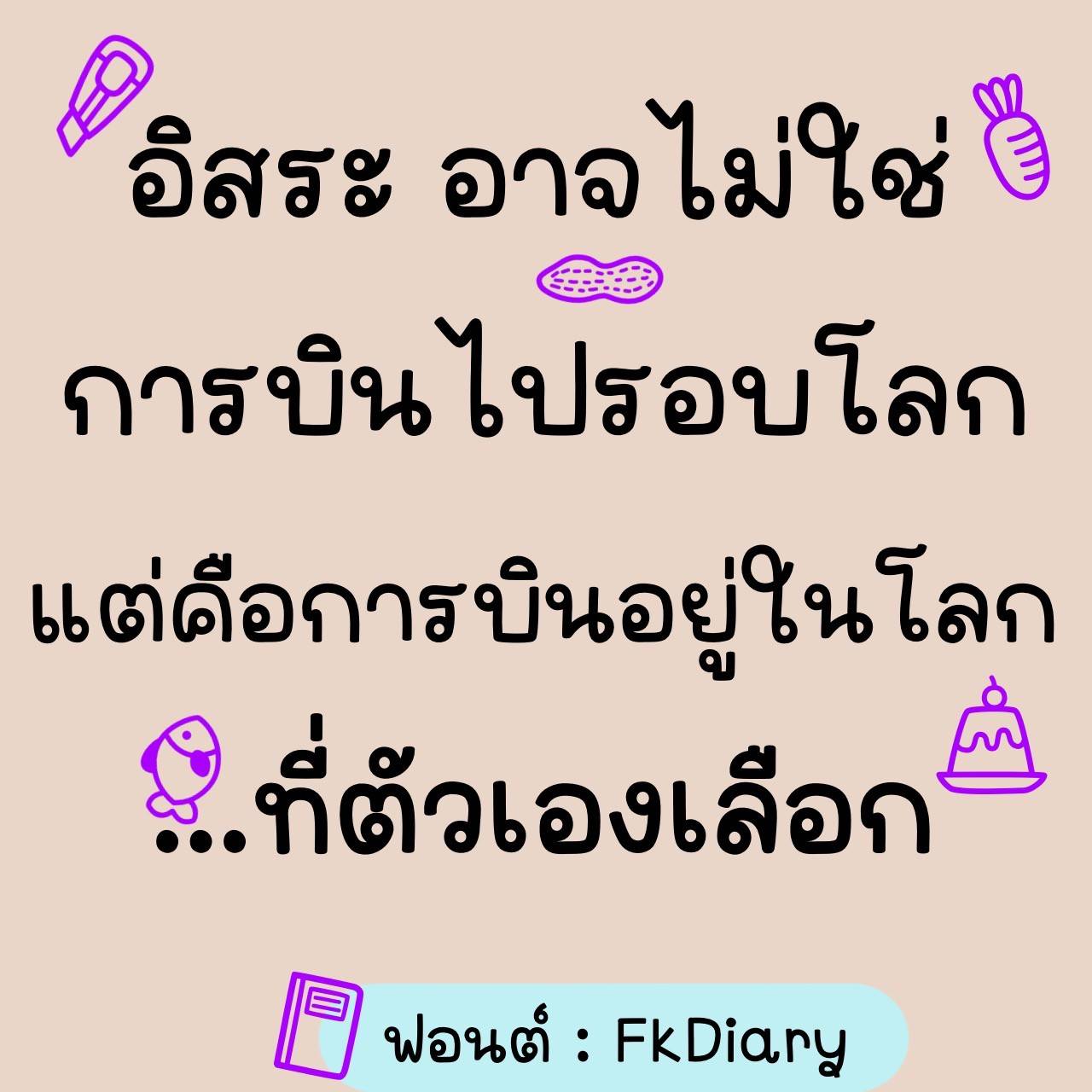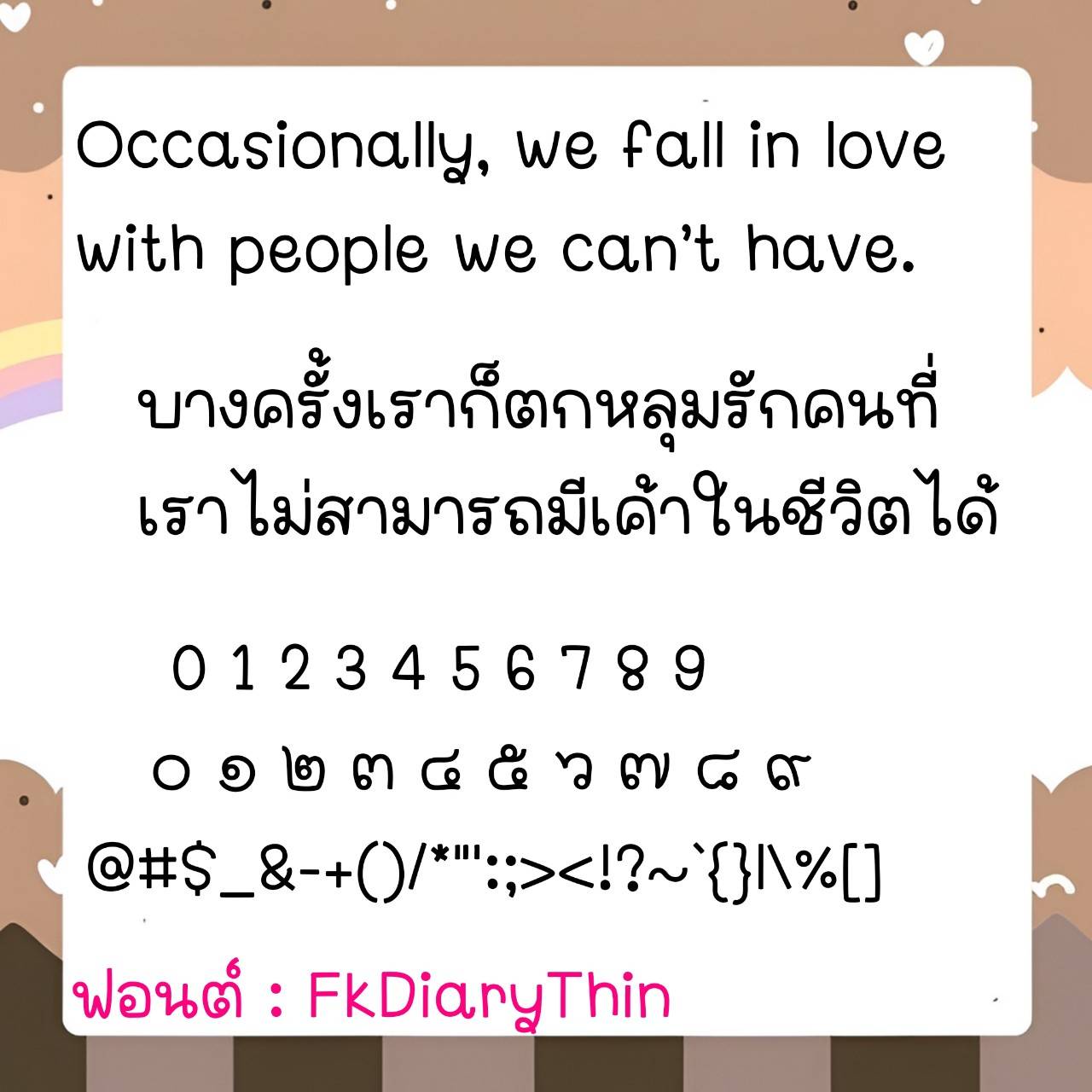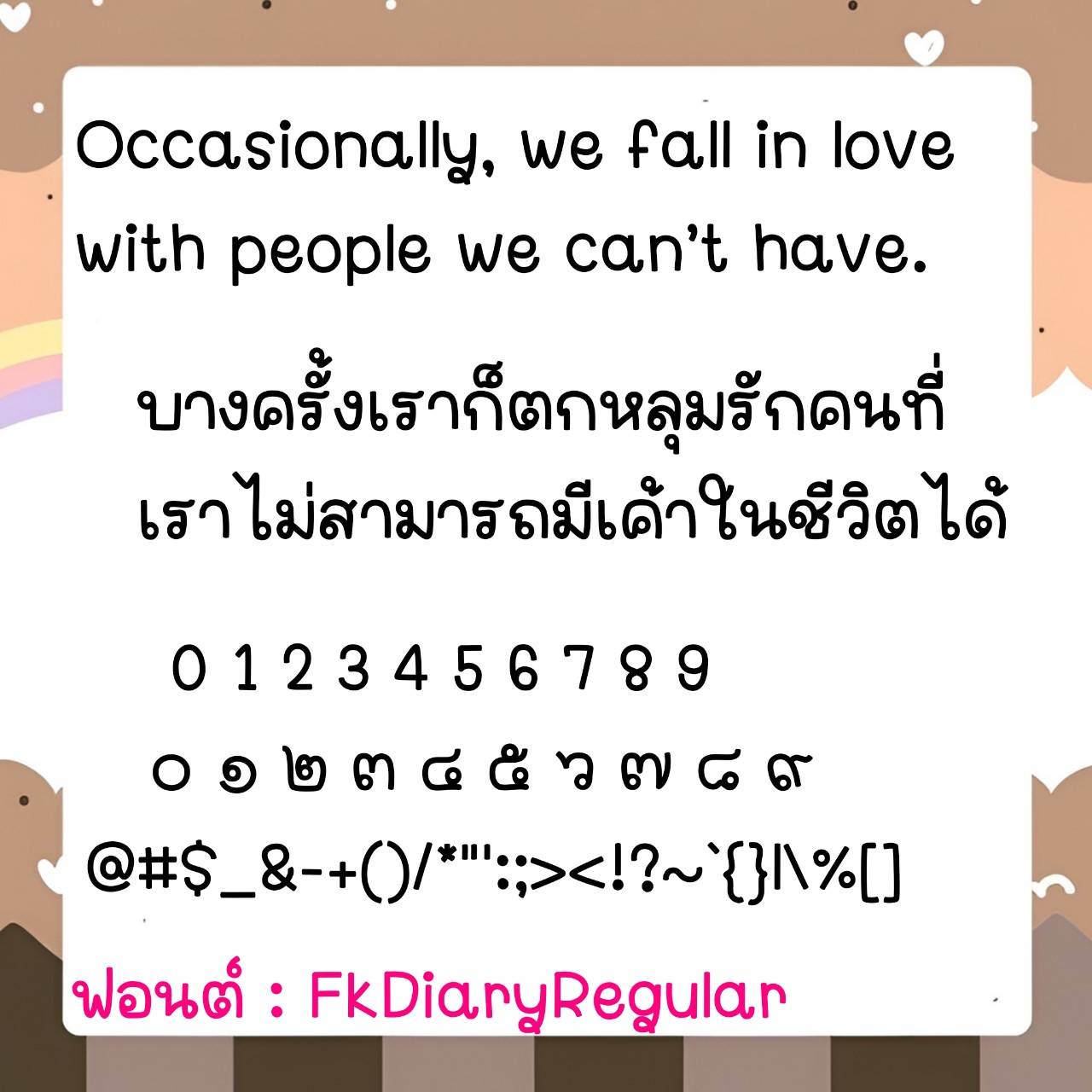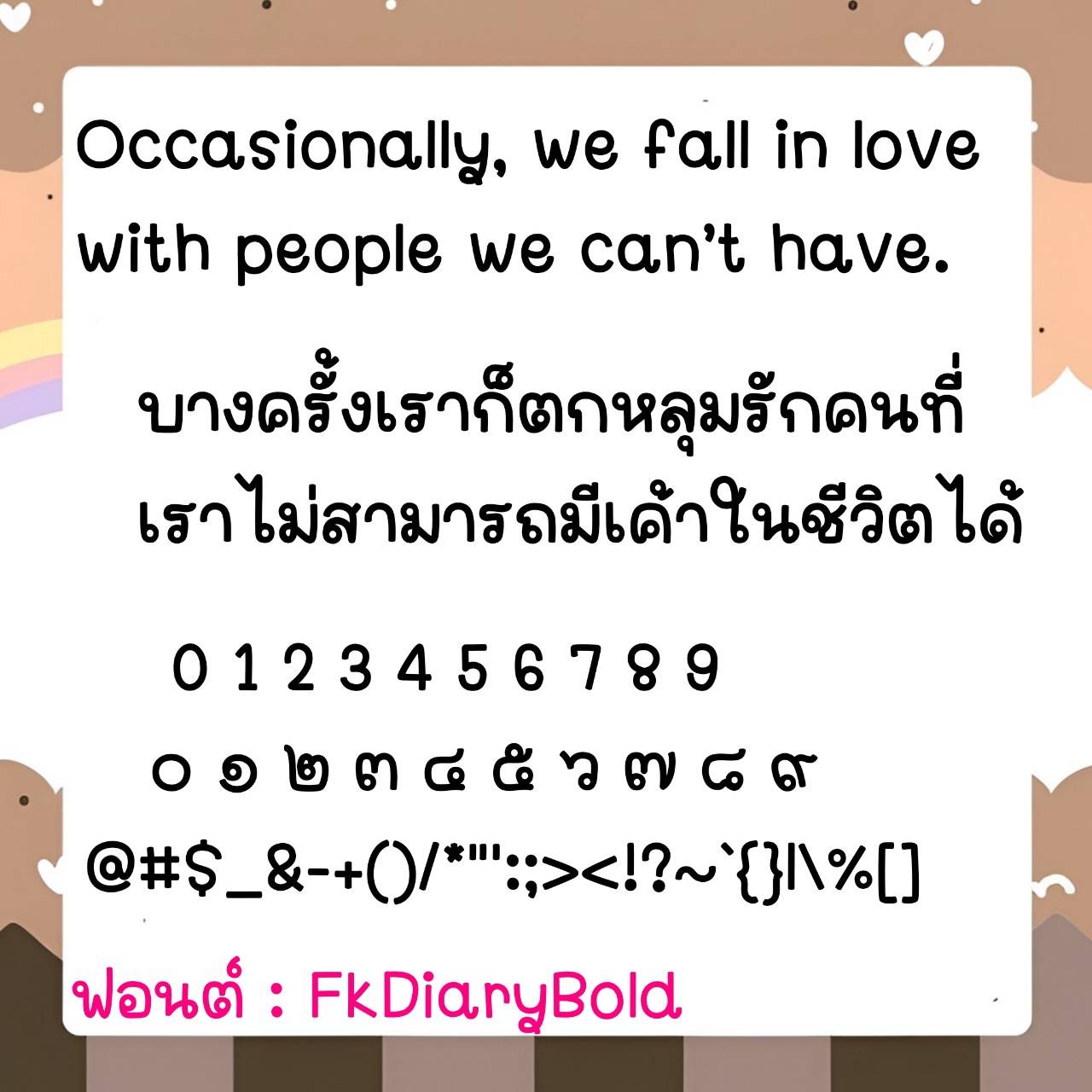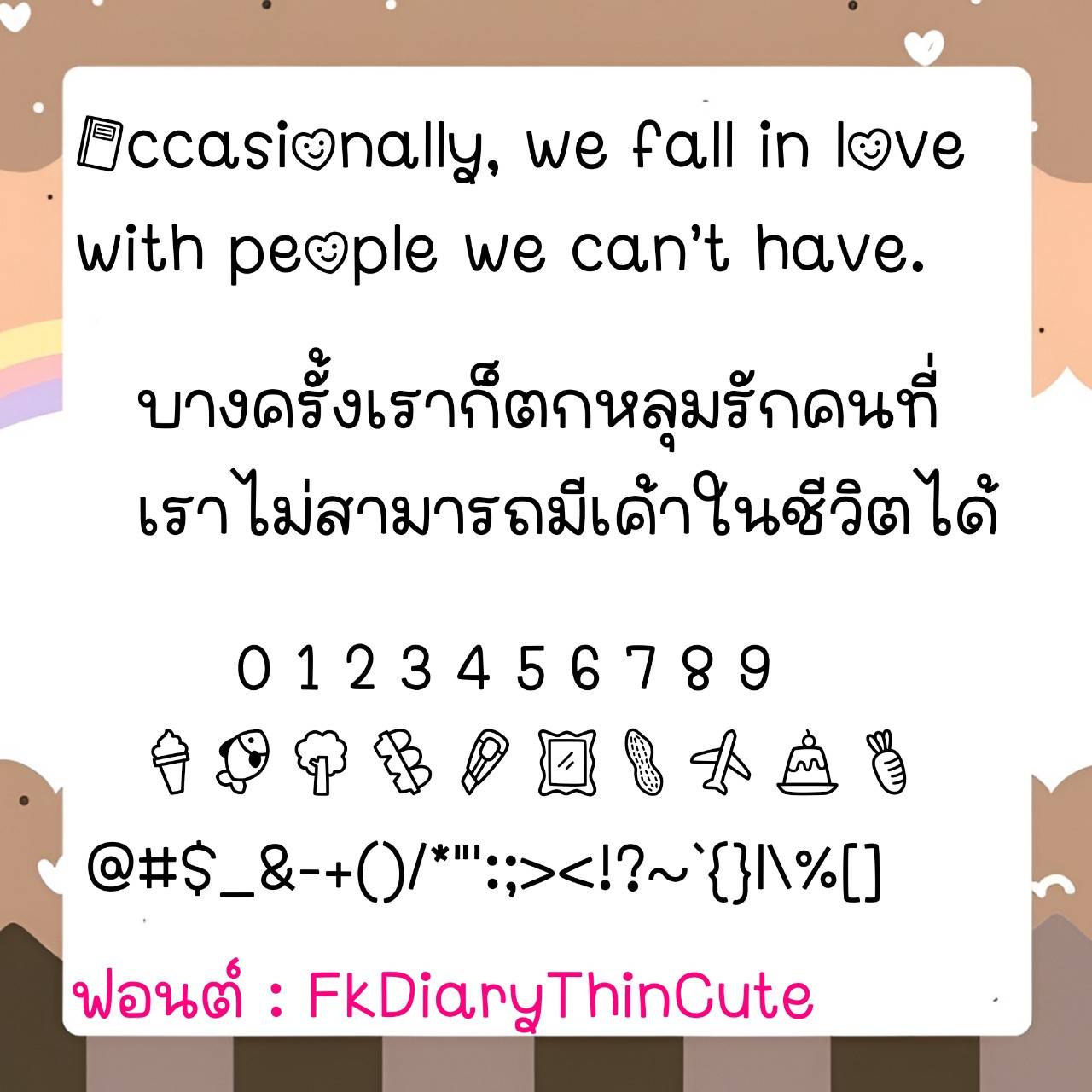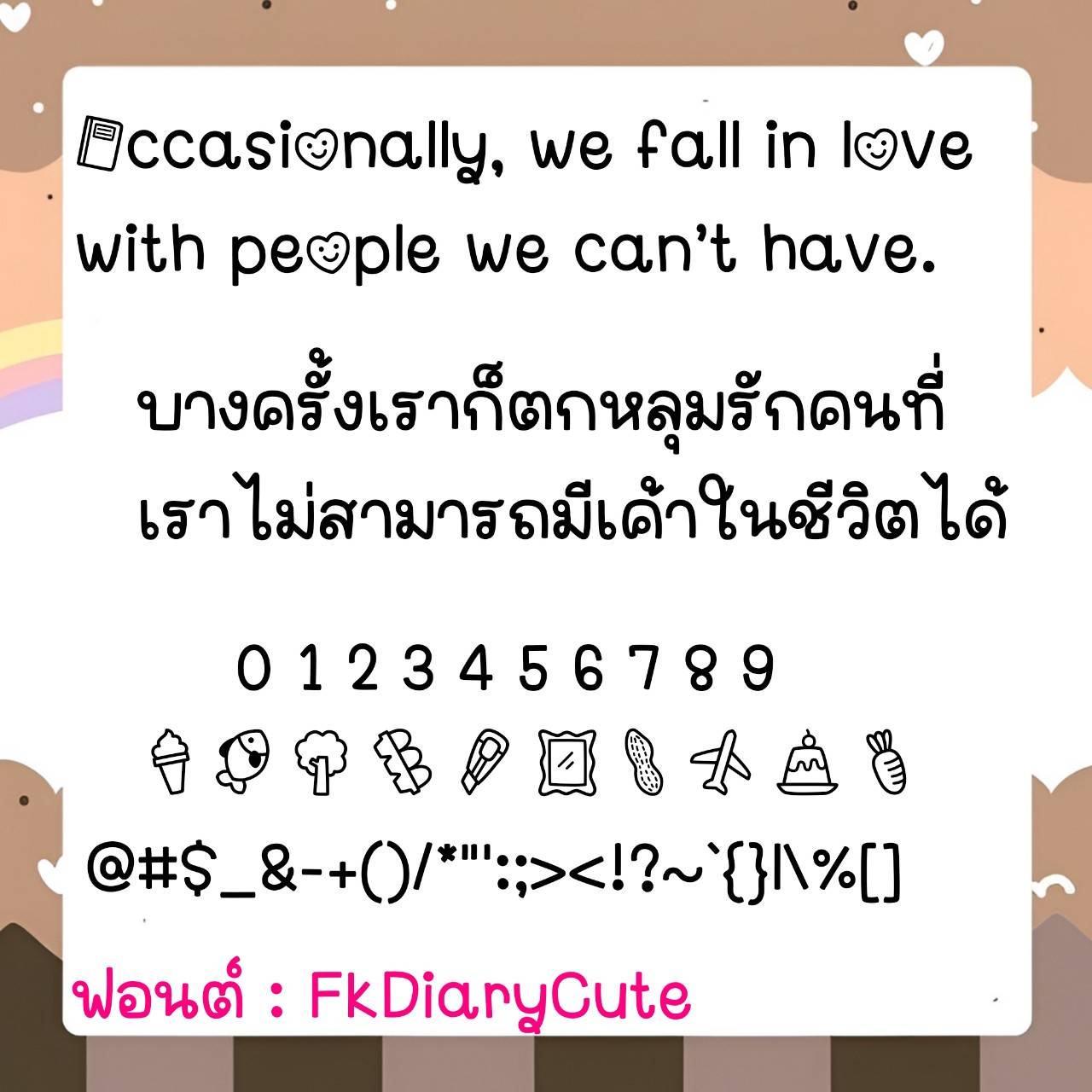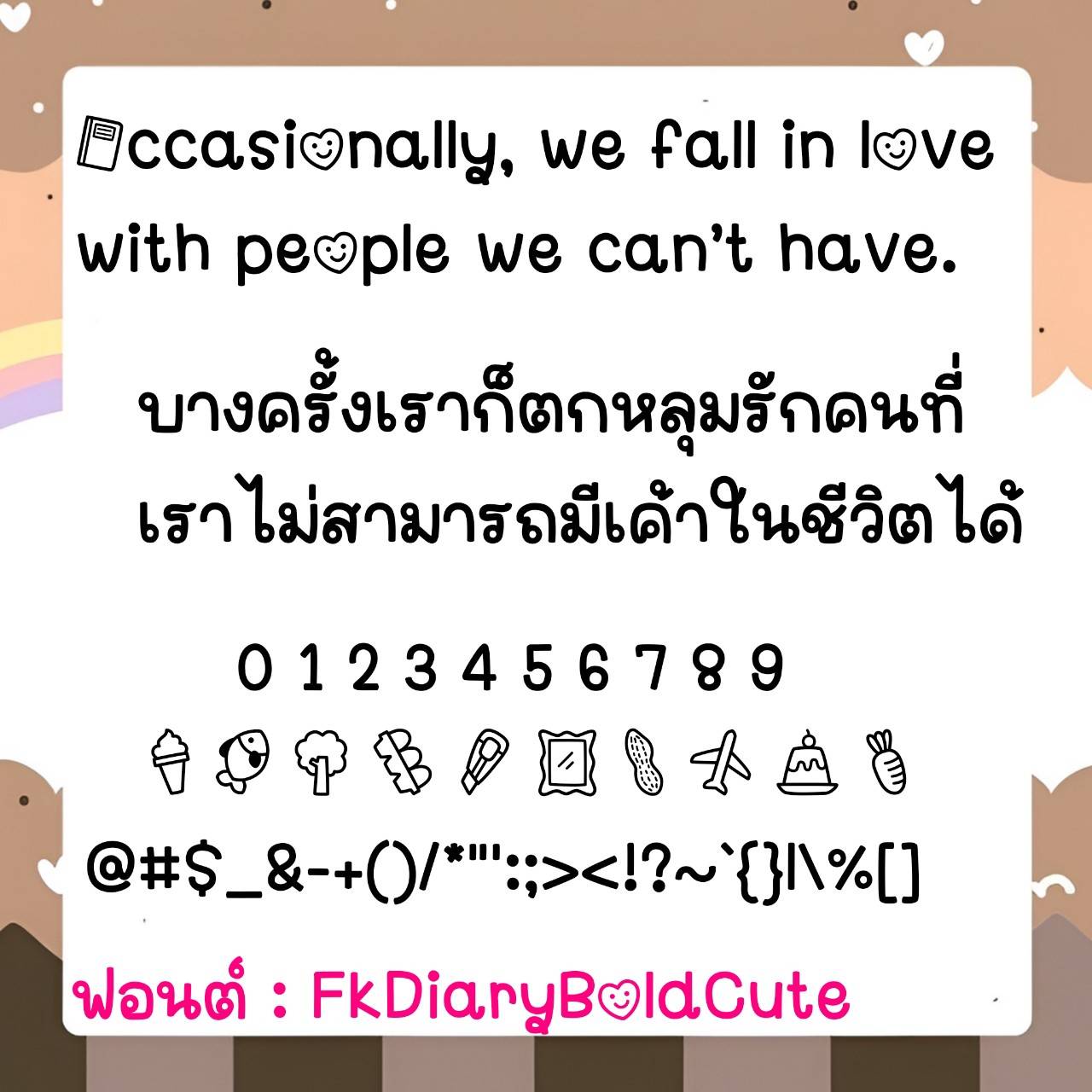
Font FkDiary
ชื่อสินค้า : Font FkDiary 💚
🔸 ฟอนต์ลายมือเส้นปลายตัด สไตล์วัยรุ่น ตัวอวบอ้วนน่ารัก เน้นอ่านง่ายสบายตา และยังมีไฟล์อิโมจิน่ารักๆ ที่ใช้แทนเลขไทยให้ด้วยค่ะ 🥰💙
🔹 Handwritten font with truncated lines, teenage style, chubby and cute characters, easy to read and comfortable to the eyes. There is also a file of cute emojis that can be used instead of Thai numbers. 🥰💙